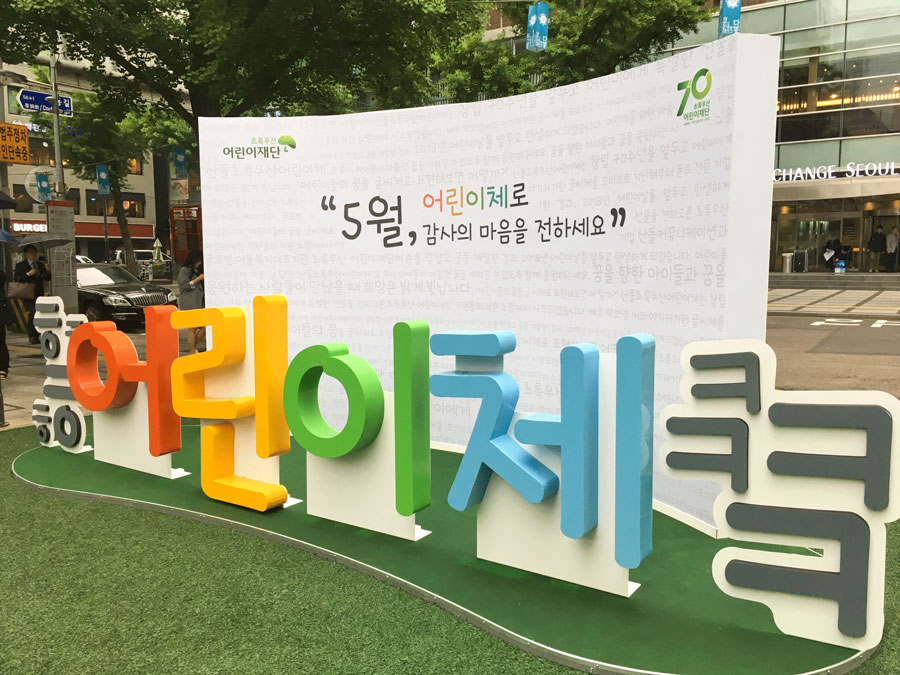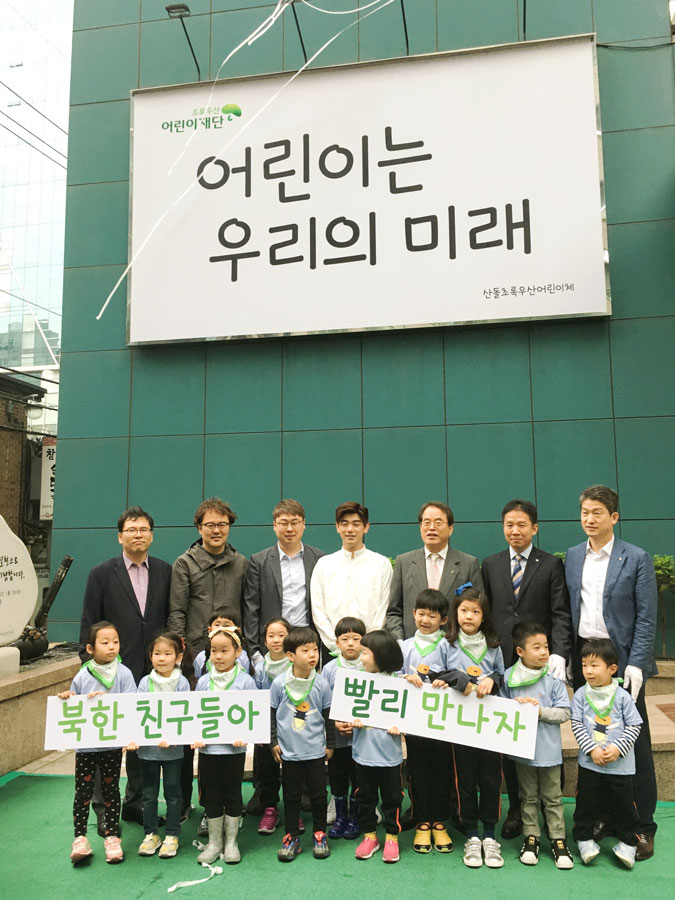
초록우산어린이재단, 어린이날을 맞이해 산돌초록우산어린이체 배포
초록우산어린이재단이 지난 5월 2일 가수 에릭남과 함께 어린이날을 기념하며 ‘산돌초록우산어린이체’를 무료 배포하고, 산돌초록우산어린이체로 꾸며진 시민 참여 공간을 열었다.
산돌초록우산어린이체는 어린이재단이 창립 70주년을 맞아 제작한 무료 폰트다. 폰트를 사용할 때마다 어린이를 생각하자는 취지에서 개발되으며, 누구나 무료로 사용이 가능하고 복사 및 재배포도 자유롭다. 배우 박보영의 손글씨를 재능기부 형태로 제공받아 폰트 회사 산돌커뮤니케이션이 제작을 맡았다.
특히 5월 2일 행사에서는 초록우산어린이재단의 건물 현판을 산돌초록우산어린이체로 교체하는 현판식도 함께 진행되었다. 현판은 상시 공개되어 있으며, 재단 본부 앞 시민 참여 공간은 5월 한달 간 개방된다.
한편 함께 참여한 가수 에릭남은 어린이체 시즌2의 프로젝트에 참여하며, 향후 세계 어린이날에 맞춰 영문이 강화된 어린이체 시즌2를 선보일 예정이다.